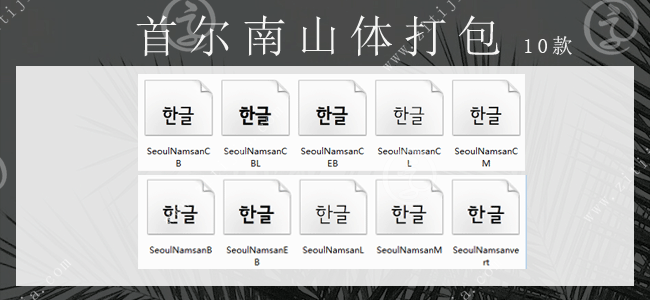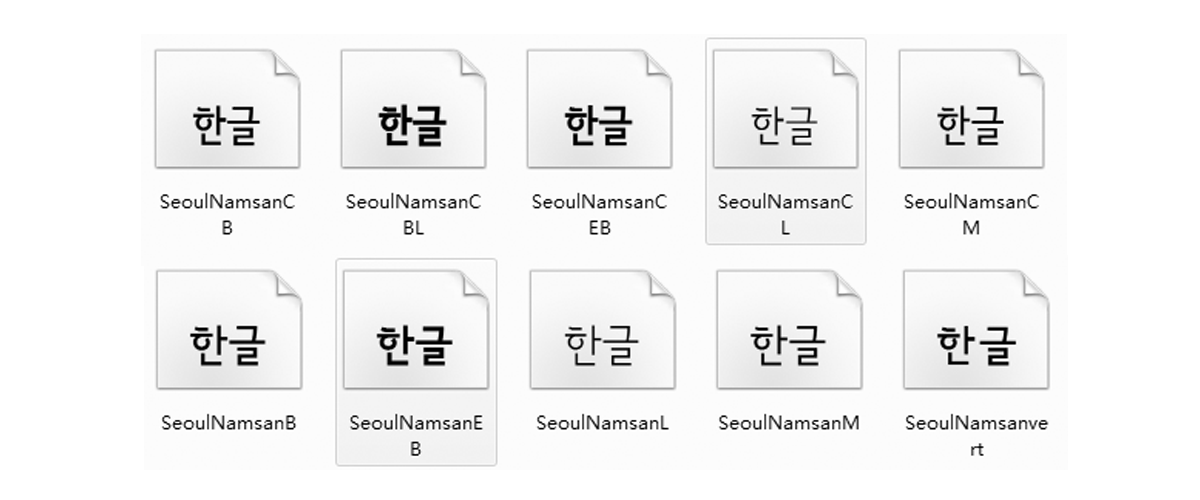
字体作者:佚名
字体家族:首尔南山体
书体类型:手写/印刷类
字体作者:首尔政府(韩国)
首尔市为广泛使用首尔的固有字体,提升城市认同性与品牌价值而开发出明体系列的4种首尔汉江体(Light、Medium、Bold、Extra Bold)和哥特体系列的4种首尔南山体(Light、Medium、Bold、Extra Bold)、1种竖写体等共9种首尔字体。
首尔字体中蕴含着强韧的儒生精神与端庄的余白美,从造型上展现了韩屋的开放和瓦片的曲线美。此外,首尔字体取名时采用首尔两大代表性资源“汉江”和“南山”,更能激发市民对韩民族固有美丽语言——韩文的文化自豪感。